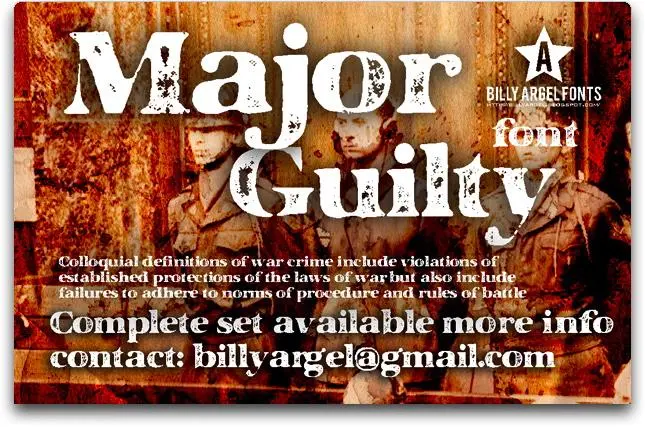
A MAJOR GUILTY Font é uma serifada que transmite elegância e sofisticação sem esforço. Seu design arredondado e marcados por Hamilton, criou um recurso visual perfeito para qualquer projeto gráfico. Suas linhas sóbrias e detalhes cuidadosos resultam em uma fonte robusta que se destaca nos textos mais importantes ou detalhados. A MAJOR GUILTY oferece um equilíbrio entre graça e seriedade, tornando-a ideal para usar em materiais institucionais ou corporativos onde uma certa gravidade é necessária. Essa fonte não apenas ressalta sua importância, mas também melhora a legibilidade geralmente associada às serifas. Com certeza, ela será um recurso vital para qualquer designer que busca uma fonte de qualidade e elegância para o seu próximo projeto.